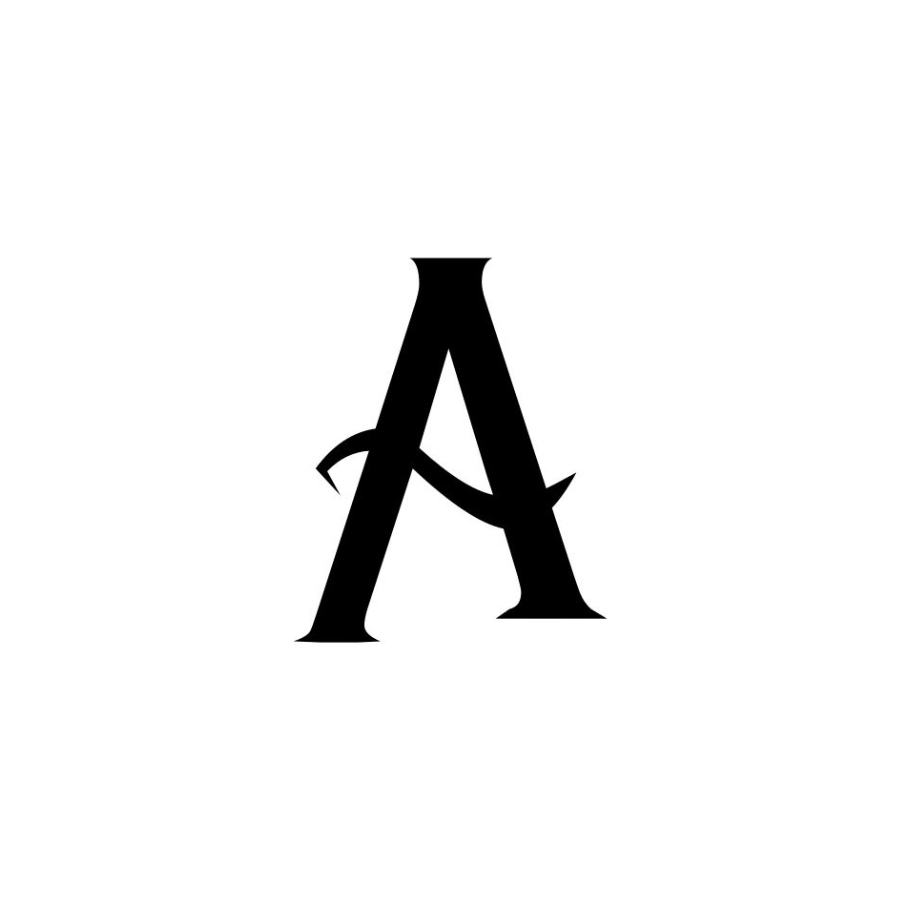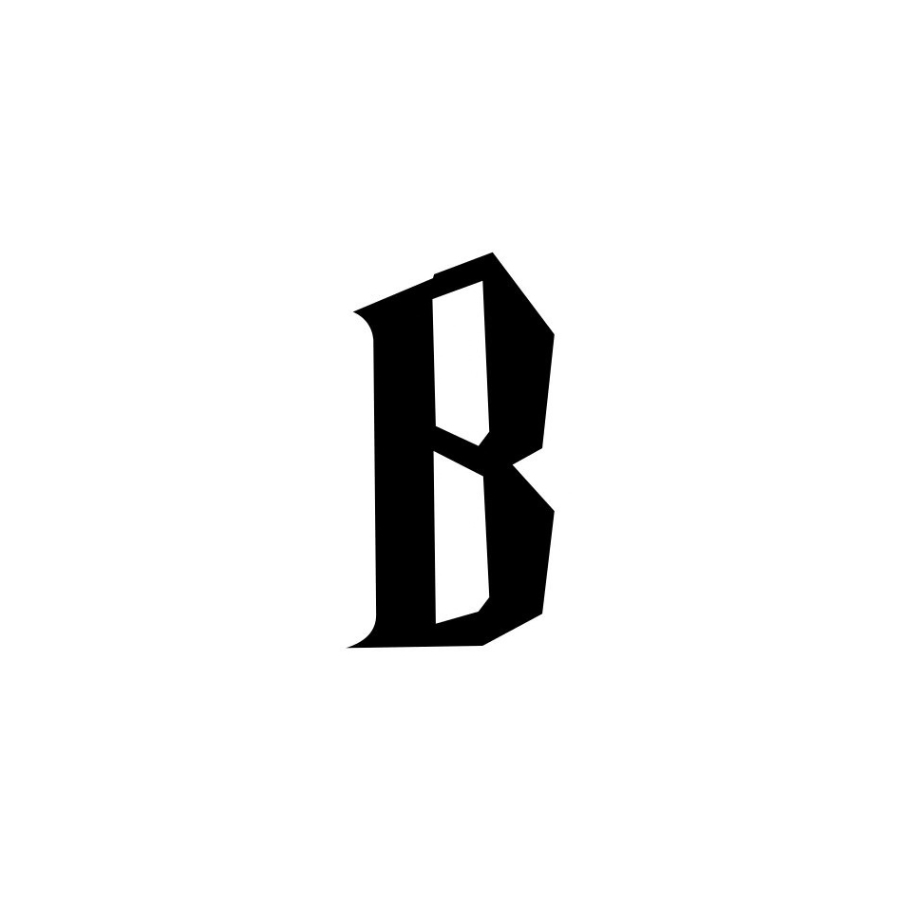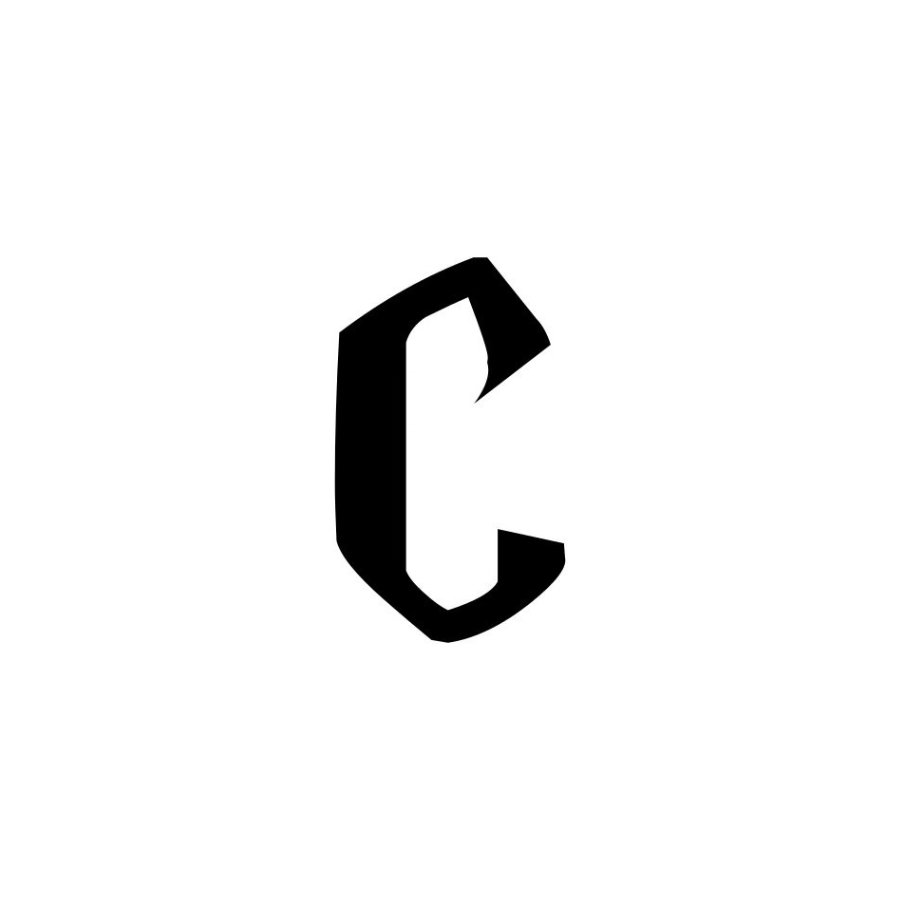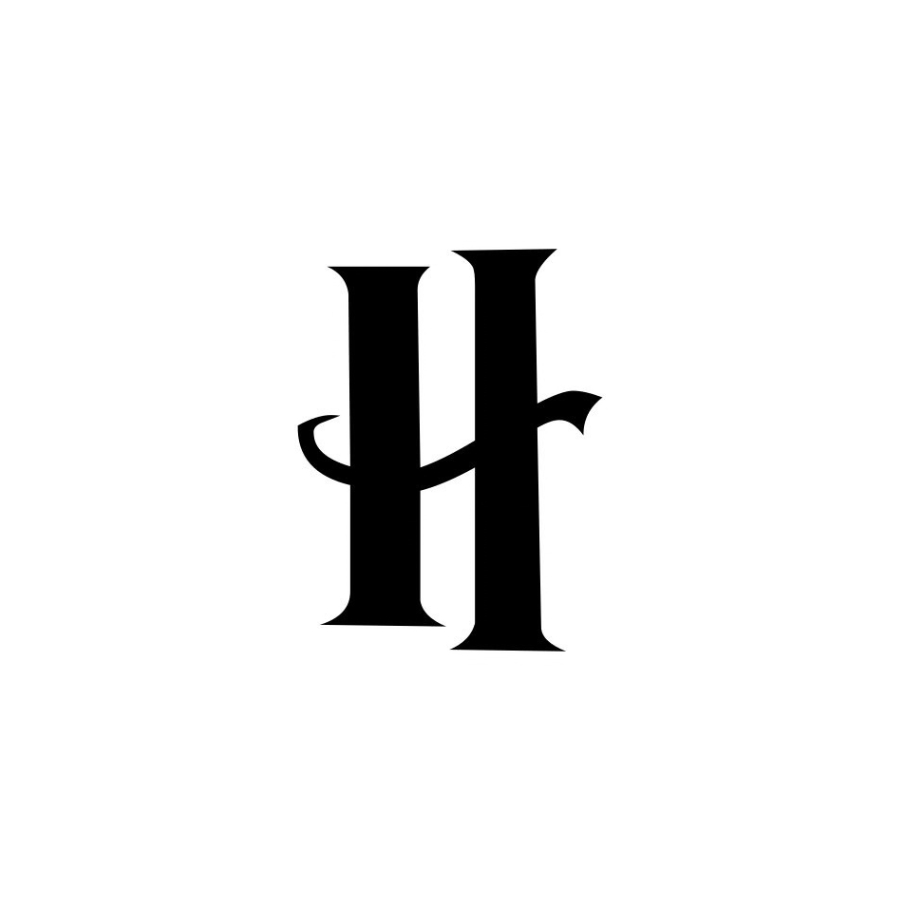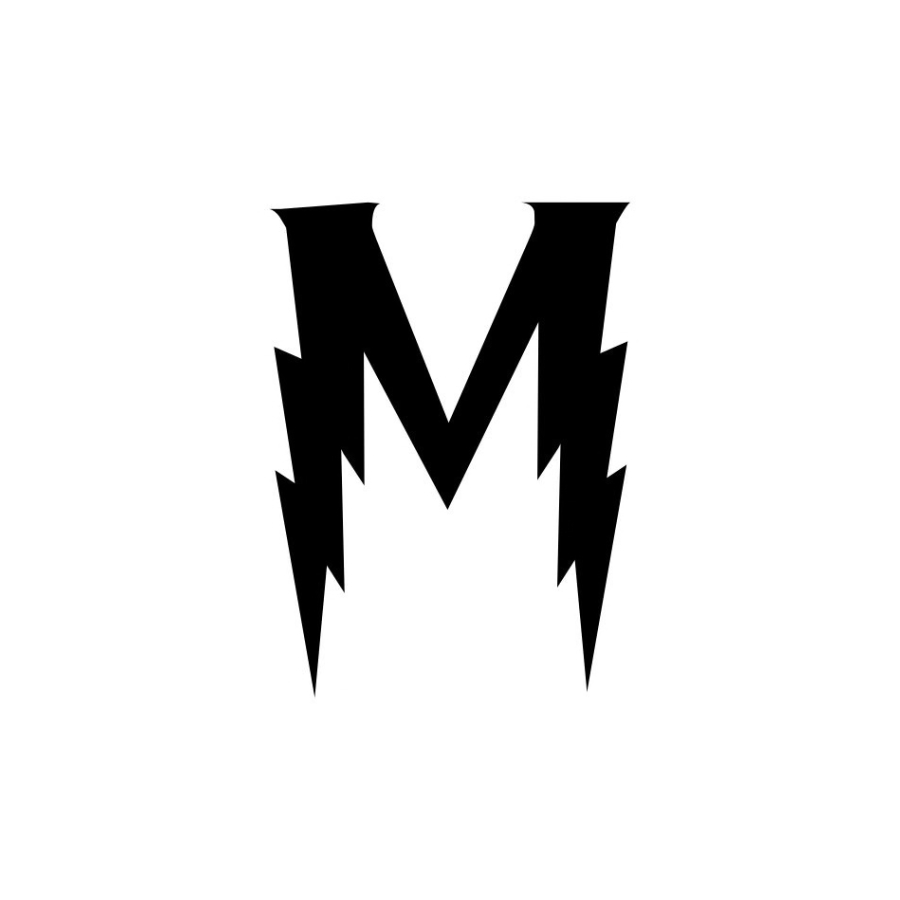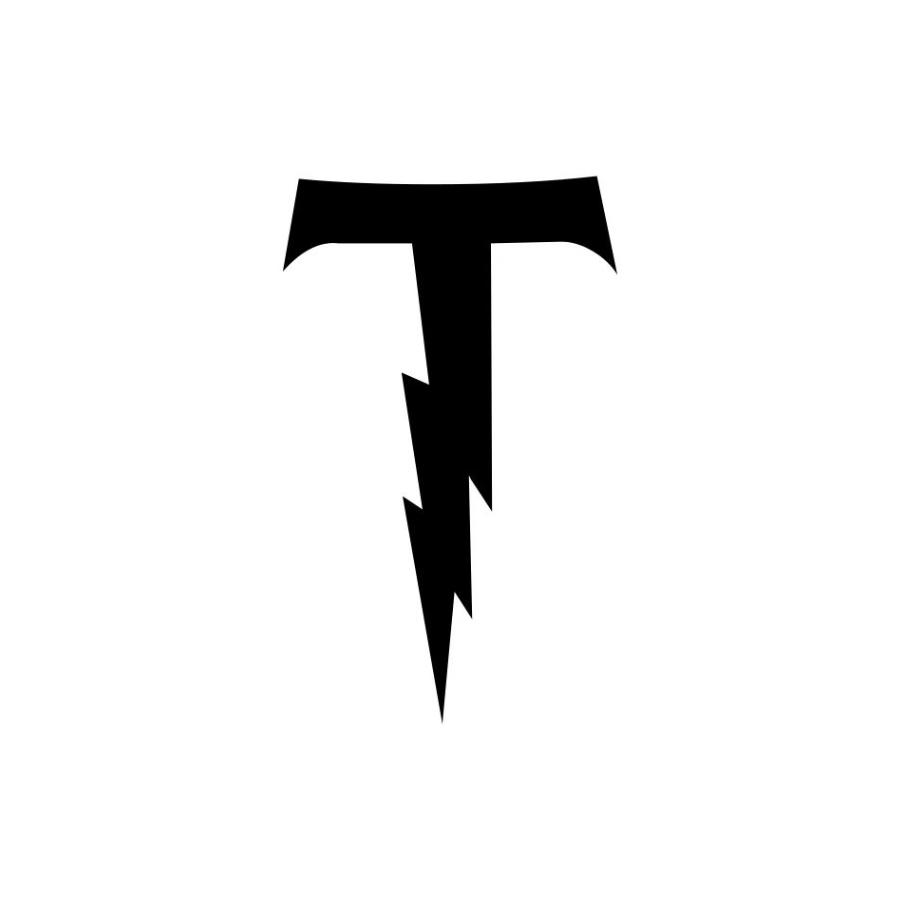
Halloween Knights Monogramm Schriftart – Gotisches mittelalterliches Grossbuchstaben-Alphabet | Cricut-kompatibel
• Diese Halloween Knights Monogramm Schriftart kombiniert einen mittelalterlichen Ritterstil mit einer dunklen Halloween-Atmosphäre. Die Buchstaben besitzen scharfe gotische Kanten, kräftige vertikale Linien und dramatische Formen, die von alten Burgen, Rüstungen und legendären Königreichen inspiriert sind. Das Design erzeugt eine geheimnisvolle und kraftvolle Wirkung, die in kreativen Bastel- und Dekorationsprojekten besonders auffällt.
• Die Schrift enthält ein vollständiges Grossbuchstaben-Alphabet (A–Z) im einheitlichen mittelalterlichen Stil. Jeder Buchstabe ist klar und kräftig gestaltet, wodurch sich die Schrift besonders gut für Monogramme, Initialen und personalisierte Namen eignet. Die stabilen Formen lassen sich sauber aus Vinyl, Papier oder Flex– und Flockfolien schneiden.
• Dieses von Halloween inspirierte Monogramm-Alphabet eignet sich ideal für thematische Dekorationen, personalisierte Geschenke, Wandbilder, Textildesigns, Tassen, Holzschilder und viele weitere kreative DIY-Projekte, bei denen ein dunkler Fantasy- oder Mittelalterstil gewünscht ist.